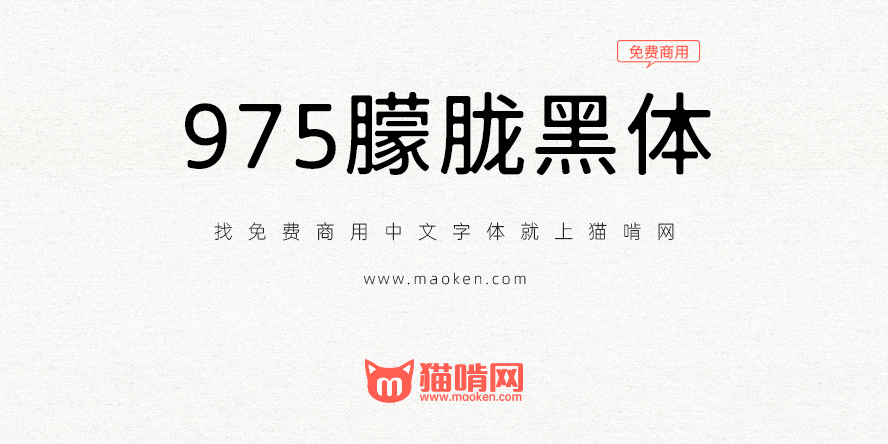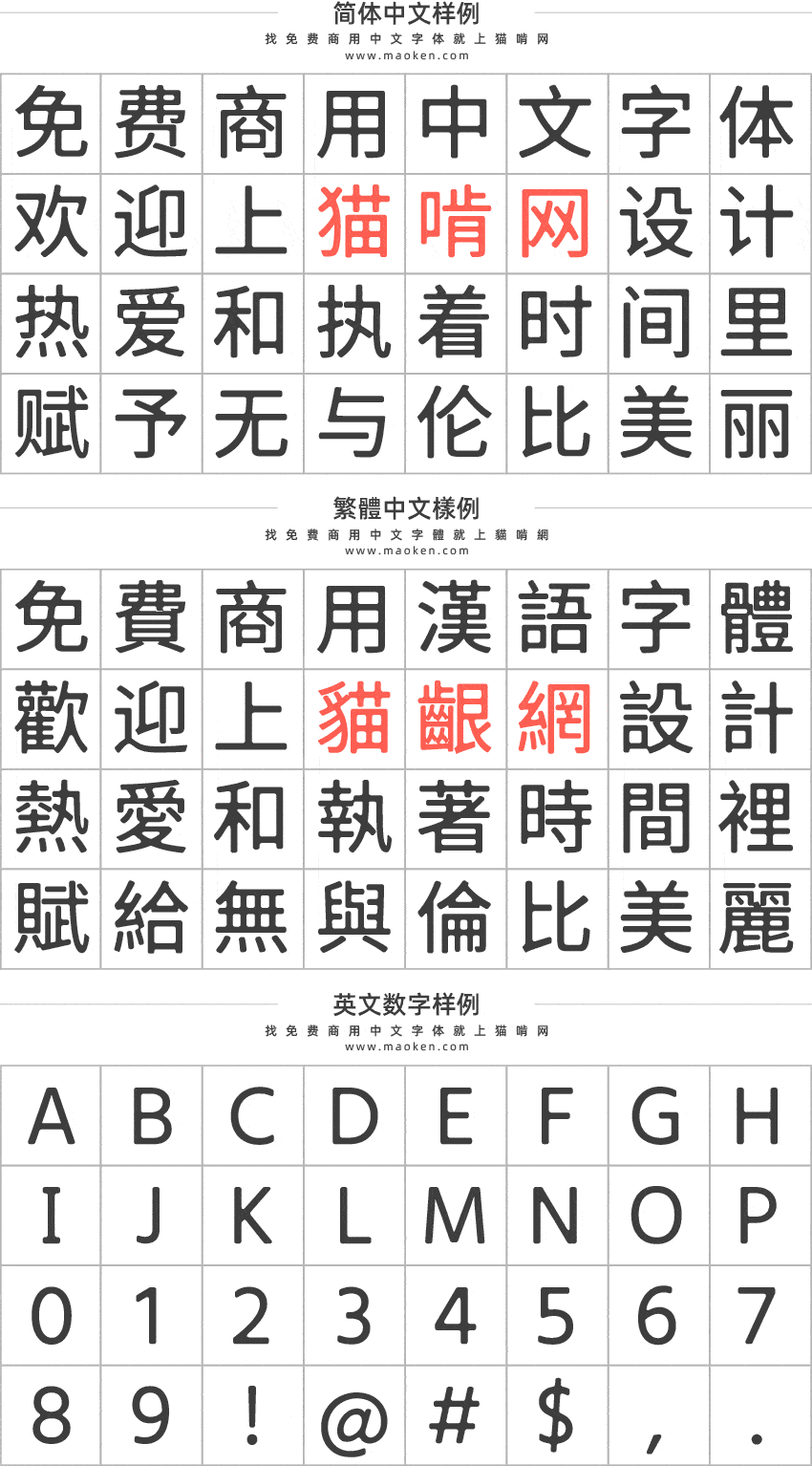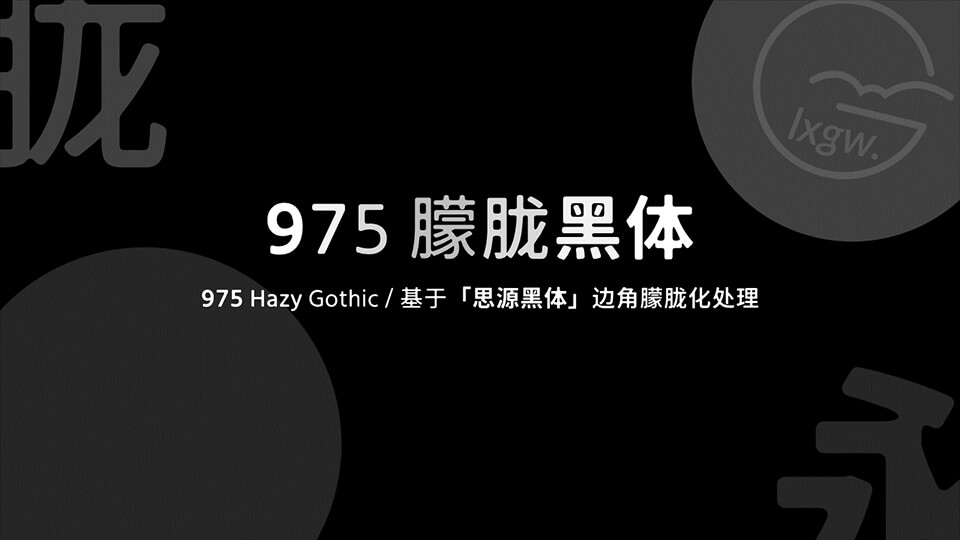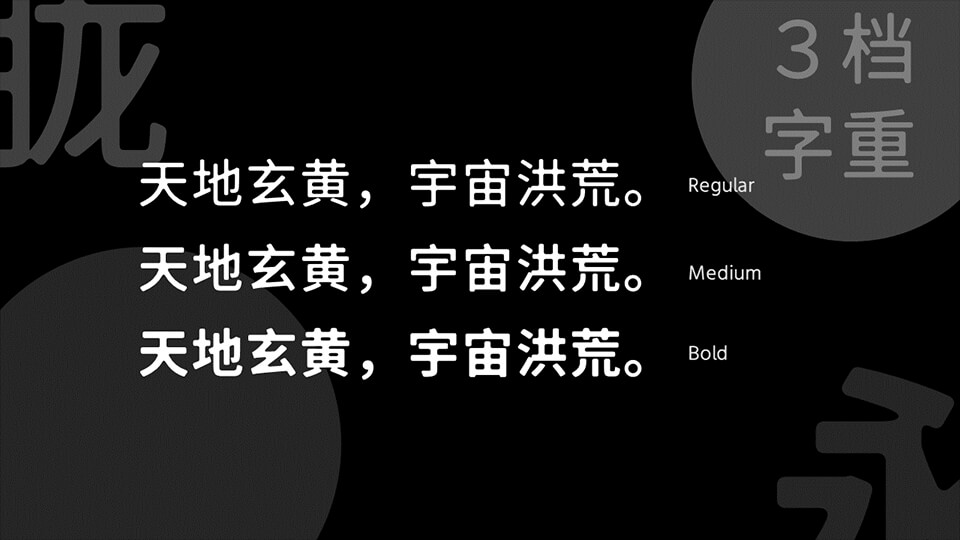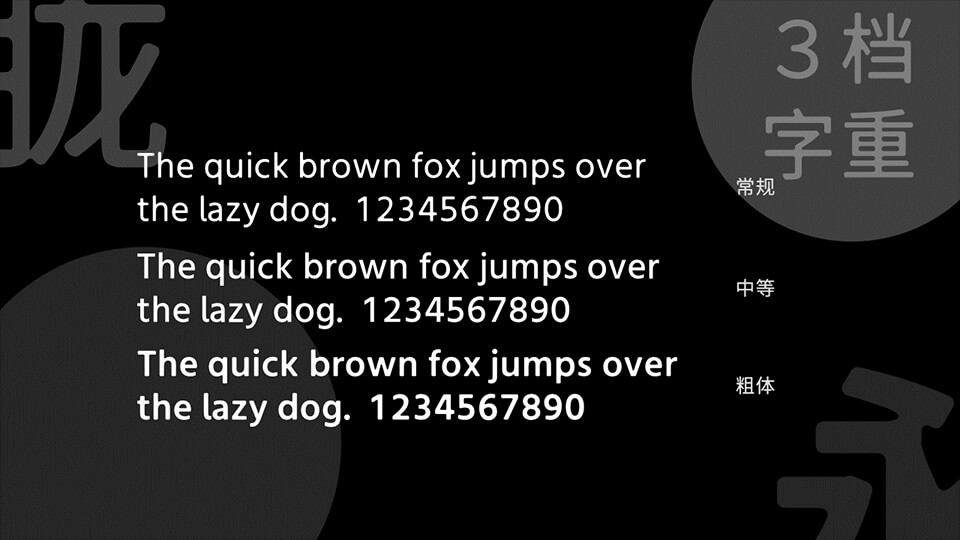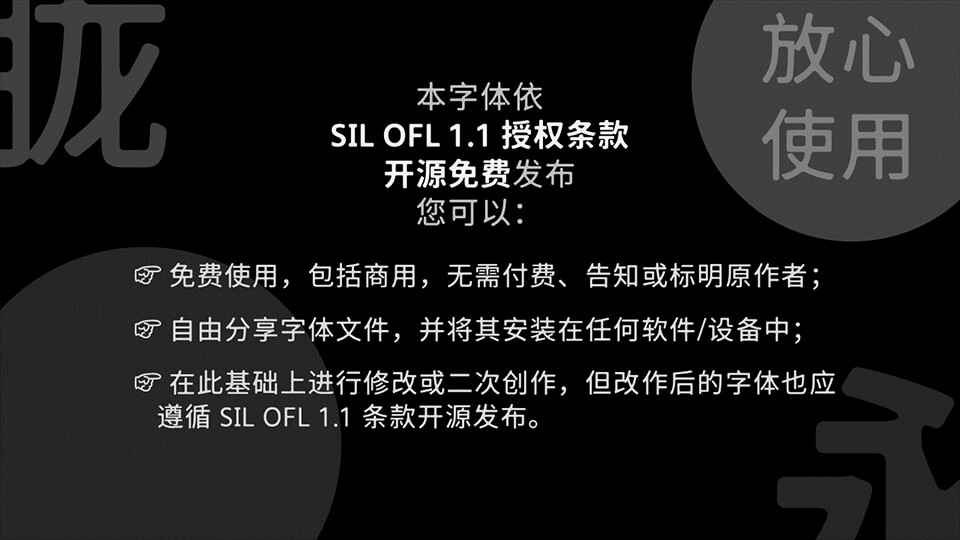
霞鹜975朦胧黑体是基于思源黑体边角朦胧化处理的一款免费商用字体。这款字体是在975黑体的基础上,内外边角加上圆角效果,使其有一种朦胧感。进行边角朦胧化之后,字体感觉像墨晕开了一样,产生别样的感受。
西文搭配经过调整处理的 GenEi Univer Sans 字体。
- 修复 400W 字重「谈」字的毛刺、「霁」字的粗细不均问题;
- 300W 字重的西文上移,使其高度与其它字重一致;
- 其它字重暂无改变。
- 基于 江城黑体 重做,修复「袱」「甭」的写法异常;
- 扩充到 5 个字重;
- 由于修改自江城黑体,本版本字体不包含韩文,节省空间。
那小写字母l能去掉勾吗?
大写字母I能不能去掉俩横?
不能。
这款字体是基于「975 黑体」直接加圆角制得的,由于「975 黑体」本身具有缺陷(如黑块、变形等),这款字体本人打算重做。临近考试,所以需要等放假了。